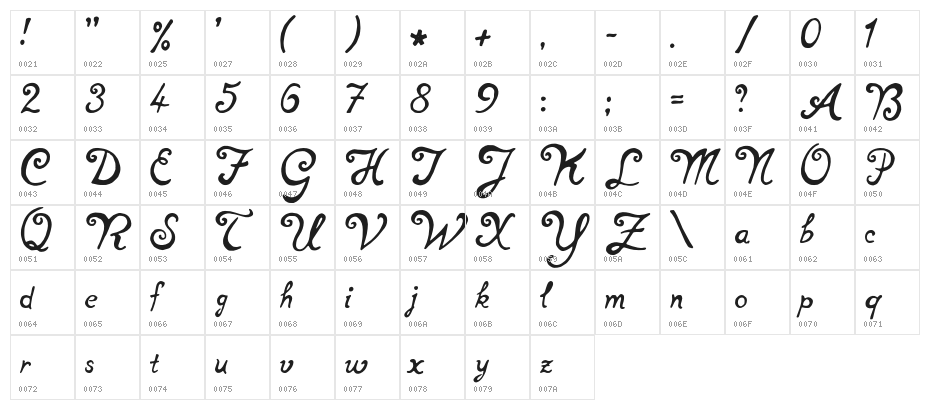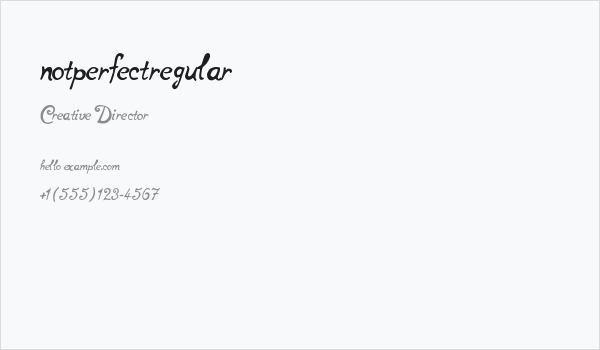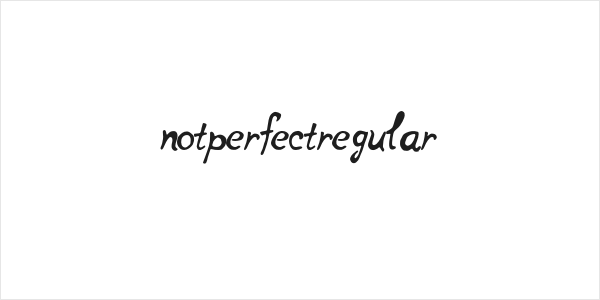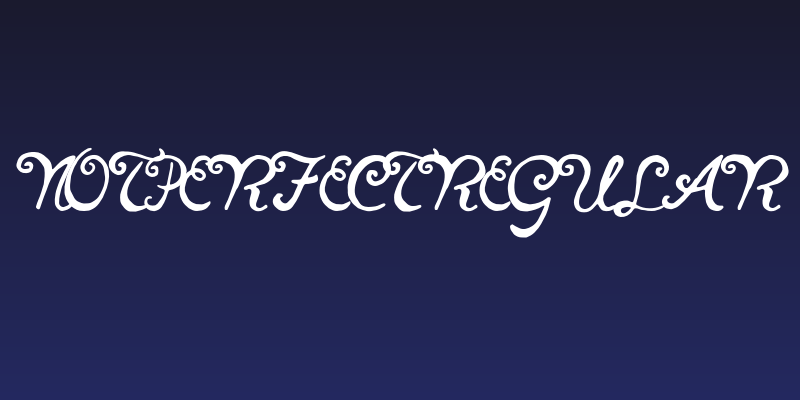
notperfectregular Font
| Caso d'uso | Logos, Invitations, Greeting Cards |
| Progetti proposti | Ideal for greeting cards, invitations, personal branding, and creative projects that require a unique, artistic touch. |